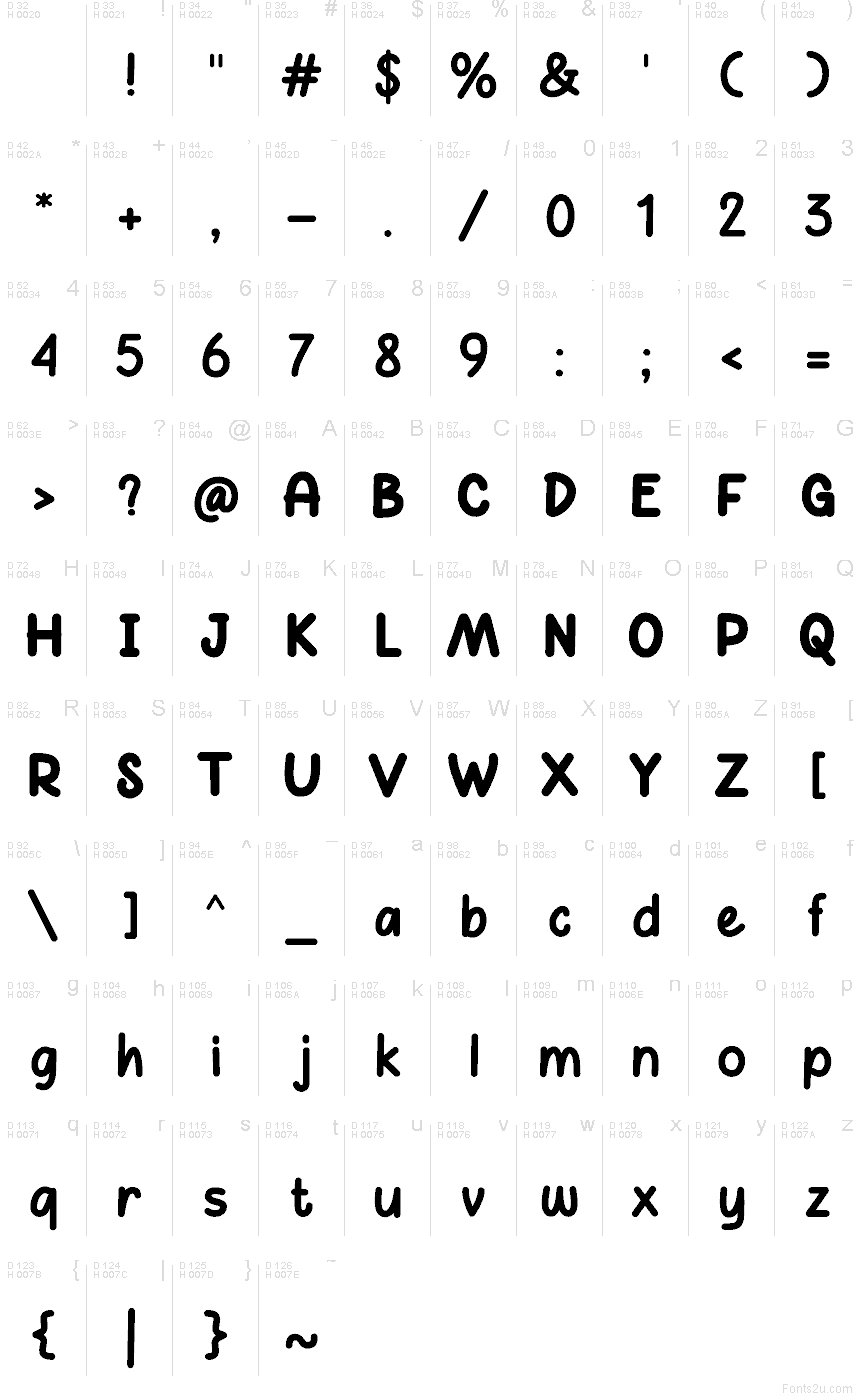
Boss cartoon
Boss cartoon від Hello Good Studio - це безкоштовний коміксний акцидентний шрифт. Округлі масивні форми та м'які кути надають йому дружнього, «мальованого» характеру. Завдяки широким кривим і лаконічним формам шрифт виглядає невимушено та легко, зберігаючи при цьому акуратність.
Boss cartoon чудово підходить для коміксних заголовків, плакатів, дитячих проектів, логотипів, упаковки та графіки для соцмереж, оскільки його округлі обриси сприймаються як життєрадісні та зрозумілі. Цей безкоштовний шрифт також ідеально підійде для наліпок і коротких промо-текстів, де потрібен живий «мультяшний» характер без зайвих відволікаючих деталей.